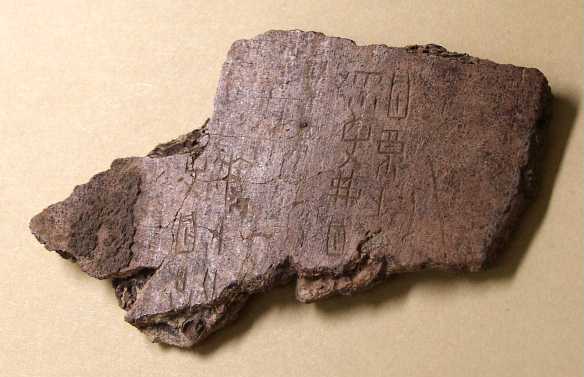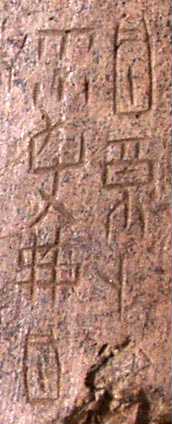
漢字>甲骨文字(贋作)
| 資料名 | 甲骨文字(贋作) |
| 文字/言語 | 漢字/漢語 |
| 材質/形態 | 骨片 |
| 大きさ | 縦43mm、横67mm、厚さ5.45mm |
中央右に「禍 鼓(支ナシ・天地逆) ト」、左に「雨 争 弗 禍」、左下右に「羊 ト 比or従」、左に「争 禍 出」とある。
左右いずれから読んでも文意が通らない。
恐らくは後の改刻であろう。
但し、左下は中央よりも摩滅が進んでおり、この両者は時期を異にした改刻の可能性もある。
画像は全景と文字部分の拡大